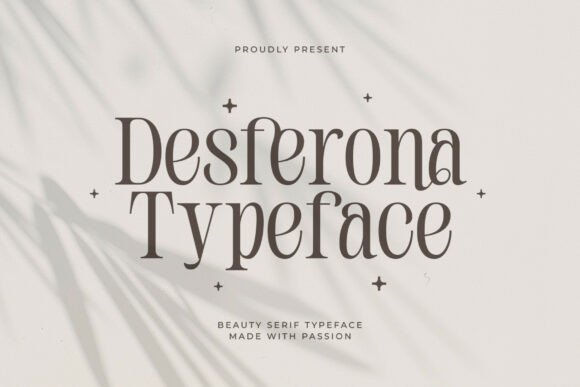
Desferona
Trouver les bons éléments de conception peut être un défi, mais Desferona propose une collection exceptionnelle qui rehausse instantanément votre travail.
Conçu avec précision, Desferona offre des vecteurs nets, une typographie fluide et une licence commerciale pour une tranquillité d'esprit.
Que vous créiez des produits POD (impression à la demande), des invitations de mariage ou des visuels pour les réseaux sociaux, Desferona est un choix idéal.